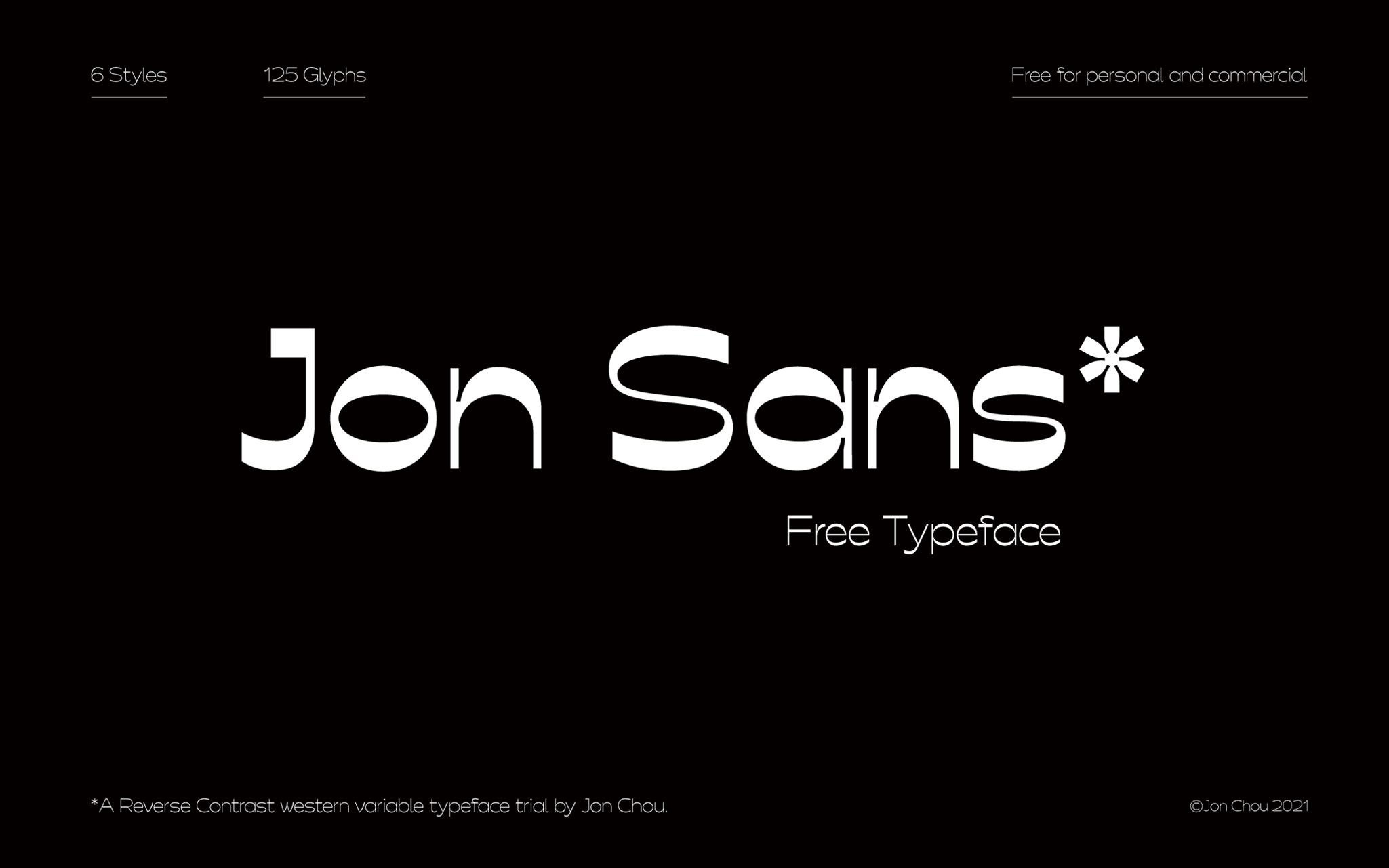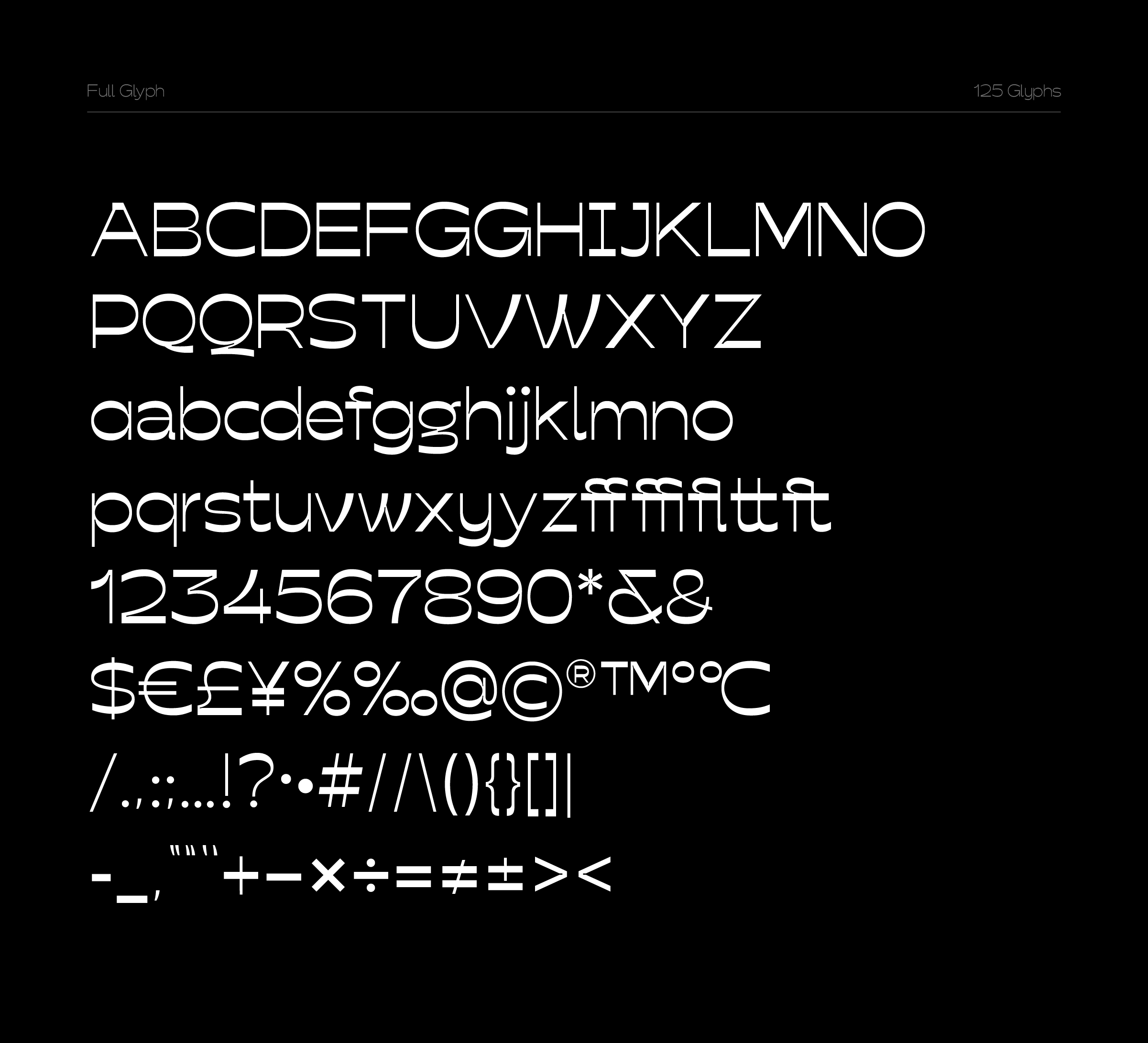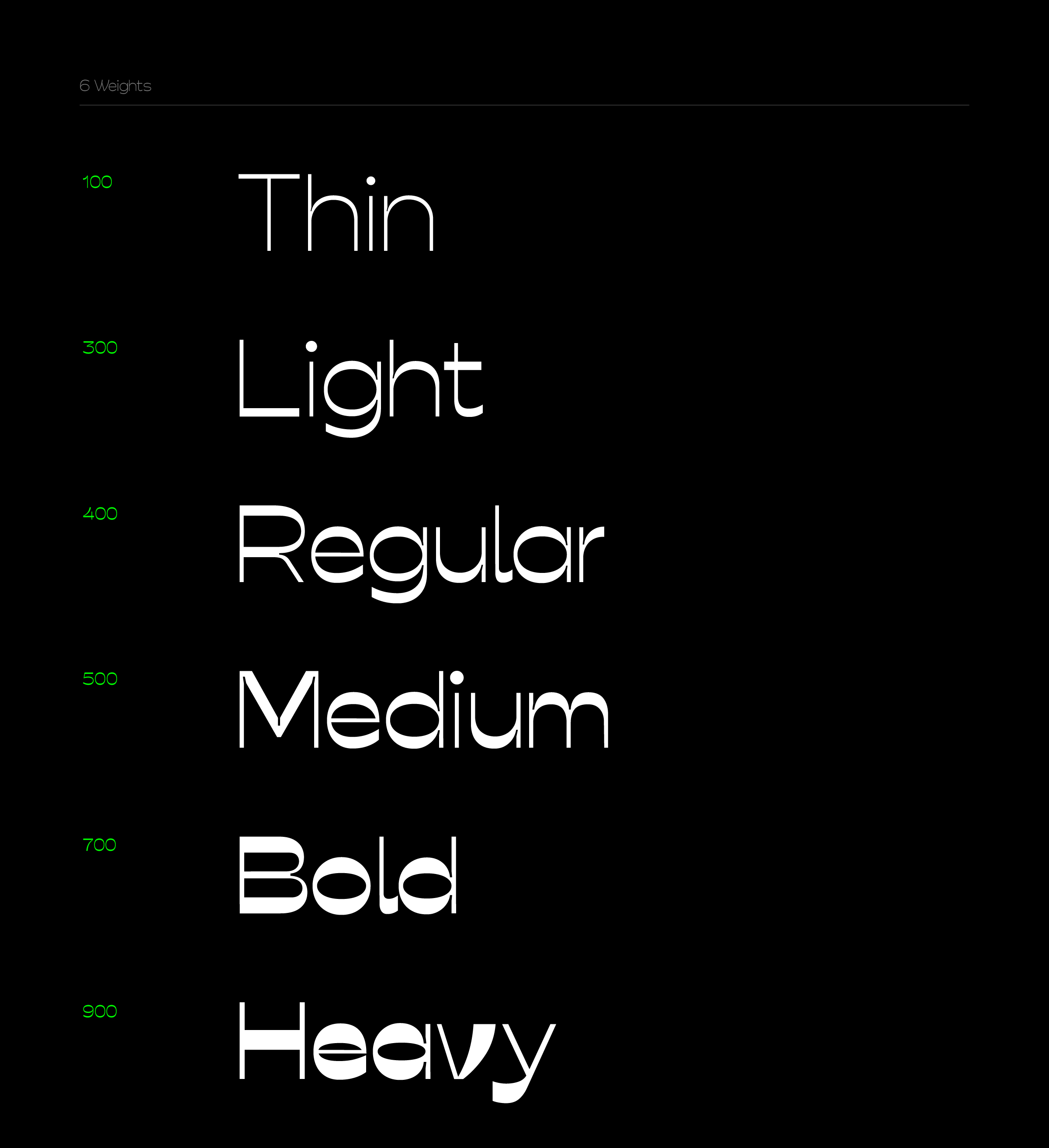
Jon Sans Trial 免费商用可变英文(西文)字体下载
Jon Sans Trial  免费商用可变英文(西文)字体下载
Jon Sans Trial是由站酷网友(JonChou)发布的一款免费商用可变英文(西文)字体,该字体风格新颖强烈,是一款“酸性”风格英文字体, 内含六个字重可用于不同场景。
Jon Sans Trial  免费商用可变英文(西文)字形预览
Jon Sans Trial  免费商用可变英文(西文)自重预览